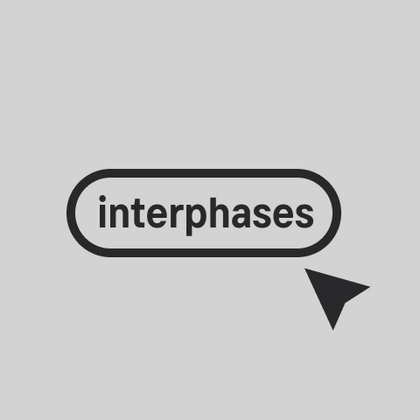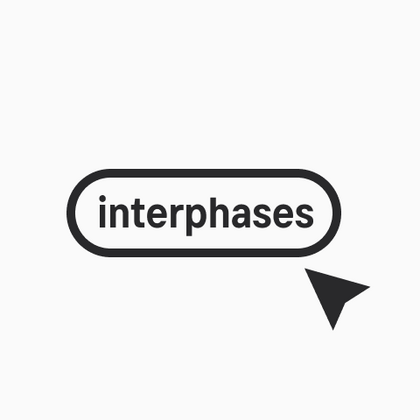
Шрифты для интерфейсов
Это специализированные гарнитуры, созданные для цифровых продуктов, где важна функциональность и удобство восприятия. Шрифты для интерфейсов — это четкие контуры, сбалансированные пропорции и адаптация к различным разрешениям экранов. В коллекции TypeType представлены современные решения с оптимизированной читаемостью — от компактных гротесков для мобильных приложений до вариативных шрифтов для адаптивных веб-сайтов, где каждый символ сохраняет четкость при любом масштабировании.
TT Glips — экспериментальный моноширинный гротеск с рукотворным характером. В маленьком кегле он кажется технологичным, но при увеличении размера проявляет округлые детали и мягкие формы.
TT Turns — геометрический гротеск с акцентными круглыми знаками и выразительными нависающими элементами. Это универсальный шрифт, который лаконично выглядит и отлично читается в маленьком размере, при этом в крупных кеглях становится акцидентным и проявляет свой характер на максимум. Он энергичный, сильный и динамичный — особенно отчётливо это проявляется в наклонных начертаниях.
TT Fellows — гуманистический гротеск с механистическими мотивами. Открытые формы, дружелюбно-нейтральный характер тонких весов и ещё более мягкий характер в жирных начертаниях.
TT Interphases Pro — неогротеск, который создавался специально для работы в интерфейсах. Среди визуальных особенностей TT Interphases Pro — плавные формы скруглений, повторяющиеся во всех элементах: благодаря им большие массивы текста читаются легко и приятно.
TT Firs Text создавался на основе обновленной в 2023 году гарнитуры TT Firs Neue. Мы сохранили эстетику скандинавского минимализма, но полностью перерисовали все выразительные элементы, сделав их более мягкими и традиционными.
TT Lakes Neue в версии 2.0 — продолжение геометрического гротеска, вдохновлённого финским функционализмом. Новая версия предоставляет больше возможностей, ведь мы не только увеличили кассовый состав и улучшили шрифт технически, но и доработали его визуальный характер.
Гарнитура TT Ricordi является коллекцией из трёх дисплейных заголовочных антикв, призванных значительно разнообразить традиционную шрифтовую палитру.
При проектировании TT Mussels мы уделили большое внимание возможности верстать большие массивы текста и можем ответственно заявить, что TT Mussels является редким видом технологических текстовых шрифтов.